学研ムック『大人の科学マガジン 小さな活版印刷機』に『秀英体』を提供
2017年12月15日に発売されたムック『大人の科学マガジン』の、付録「小さな活版印刷機」の活字として秀英体を提供しました。
金属活字を用いた活版印刷が広まった明治時代からDNPが継承してきた「秀英体」は、日本の出版文化を支えてきた歴史ある書体で、ひらがなの「い」や「こ」等が一筆書きになっているなど、クラシックかつモダンで美しいデザインが特長です。付録の活版印刷機と「秀英体」の活字によって、温かみのある手作りの名刺や紙小物が作成できます。
「学研ムック「大人の科学マガジン 小さな活版印刷機」に『秀英体』を提供
― 歴史ある秀英体の活字で、温かみのある手作りの名刺や紙小物を作成可能 ―」
「大人の科学マガジン 小さな活版印刷機」の内容
巻頭特集では、かわいくてかっこいい活版印刷の作品を紹介。また、活版印刷クロニクルのほか、「秀英体」の歴史や特徴、デジタル書体としてのリニューアル開発の取り組みも収録されています。
付録の特長
●「テキン」型の卓上活版印刷機
インキを練る。活字にインキをのせる。プレスする。この3つの動作をハンドルの上げ下げだけで操作して、印刷を行います。ムック本誌の中に、わかりやすい作り方のページがあり、印刷機の仕組みを学びながら約30分で本体の組み立てができます。
「テキン」型の卓上活版印刷機
●162個の活字
ひらがな(秀英明朝M)、数字・アルファベット(Century)がそろった162個の活字が使えます。活字台は名刺サイズで、最大135個の活字をセットした版を作ることができます。
付録の活字
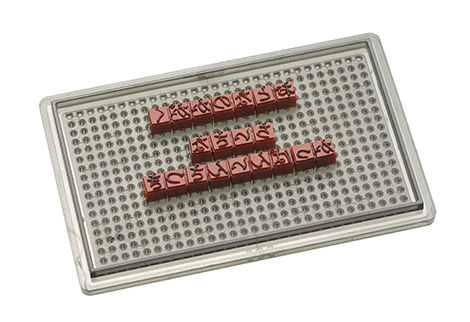
活字組み見本
●その他
自然でやわらかな風合いを持った活版印刷用のコットンペーパーや、お試し用の黒インキが入っているので、組み立て後、すぐに印刷することができます。
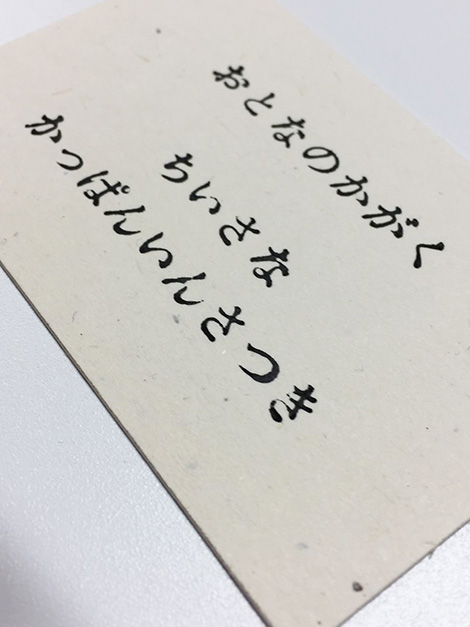
印刷見本
早速、小さな活版印刷機と秀英体の活字で、年賀のメッセージカードを作ってみました!
筆書きの風合いが美しい「秀英体」を使って、温かみのある年賀状を作成してみてはいかがでしょうか?